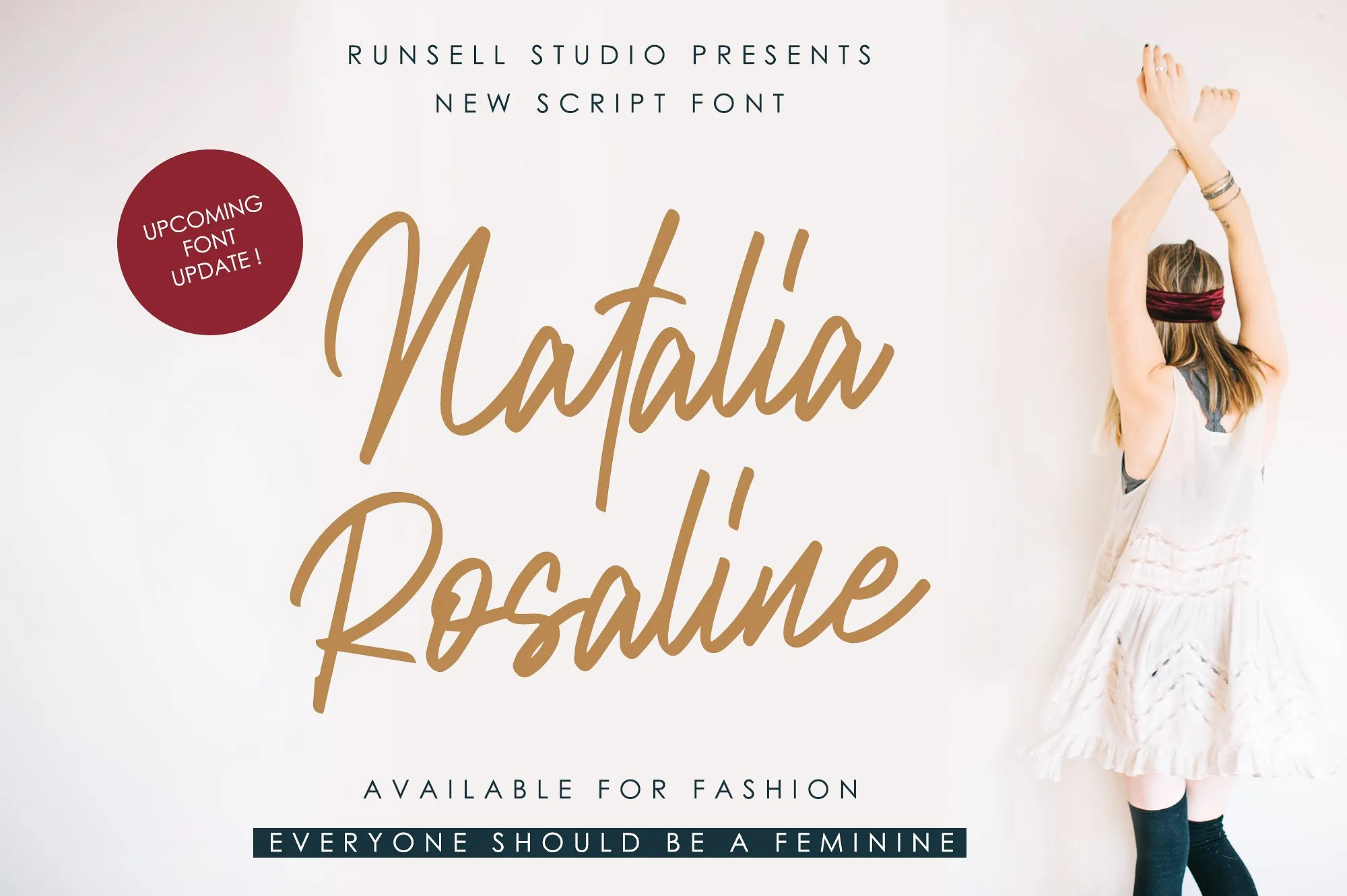
Natalia Rosaline Font Duo – Download Grátis
Afonte Natalia Rosaline é uma escolha especial para designers apaixonados por moda e criatividade. Este script tem uma personalidade única que se destaca em várias áreas do design, incluindo logotipos de marcas, blogs online e websites, embalagens e identidades corporativas. Com seu toque feminino, a font Natalia Rosaline oferece um desafio emocionante para criar designs memoráveis e inovadores. A grande novidade é que esta font estará atualizada com novos recursos e outros interessantes fontes para os usuários adicionalmente. O designer Hamilton criou uma fonte versátil que se adapta a diferentes tópicos do design, permitindo aos criativos explorar seu potencial inexplorado. Esta font é não apenas um recurso útil em sua coleção de recursos gráficos, mas também uma ferramenta para expressar sua personalidade e estilo único. Com Natalia Rosaline, você pode adicionar um toque diferenciado ao seu trabalho, tornando-o mais atraente e memorável.